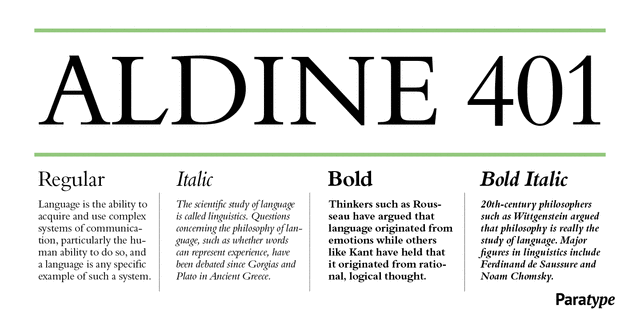
Альдин 401 представляет собой классический шрифт Бембо в трактовке фирмы Битстрим. Основан на рисунке шрифтов, нарезанных Франческо Гриффо для книги итальянского гуманиста Пьетро Бембо De Aetna («Об Этне»), написанной в Венеции и напечатанной там же Альдом Мануцием в 1495 году. Антиква Гриффо считается одним из первых шрифтов старого стиля, образцом для Гарамона и предшественником европейских текстовых шрифтов двух следующих столетий. Современный Бембо был разработан в 1929 году в фирме Монотайп под руководством Стенли Морисона. Шрифт до сих пор остается популярным, особенно в книжном дизайне, благодаря благородным пропорциям, классической простоте и отсутствию каких-либо ненужных, «цепляющих» особенностей. Курсив основан на работах каллиграфа эпохи Возрождения Джованни Тальенте. Уместен как текстовый шрифт в литературе самой разной тематики. Кириллическая версия разработана Изабеллой Чаевой и выпущена компанией ПараТайп в 2008 году.
Ассоциации c семейством Aldine 401Качества и характер:
благородный, консервативный, традиционный, классический, пафосный, повествовательный, художественный, серебристый, образованный, острый, мастерский, архитектурный, исторический, гуманитарный, серебрянный, динамичный, комильфо, вежливый, изящный, красивый, аккуратный, уважительный, прилежный, тактичный, образцовый, убедительный, логичный, твердый, поучительный, авторитетный
библиотека, искусство, музей, литература, эстетика, проза, поэзия, музыка, архитектор, вино, образование, серебро, концерт, комильфо, финансы, симфония, живопись, обед, ужин Стилистика: